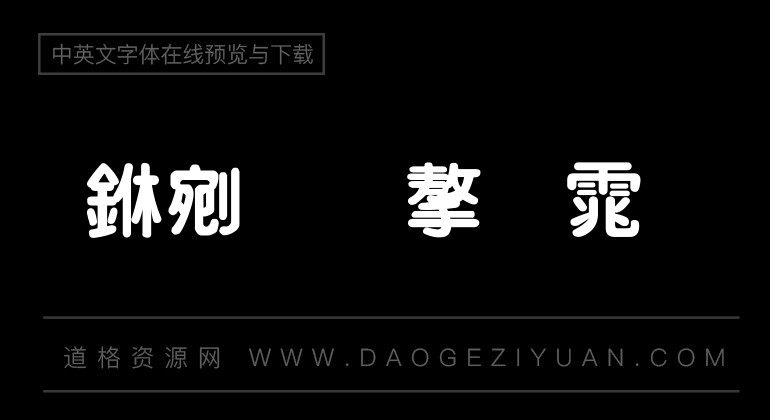
书法家叠圆体
书法家叠圆体,又称“叠圆体”,是由中国书法家叠肖拉克(1890-1965)创作的一种书法字体。它是以“叠”字为主体,将“叠”字的横线、垂线和拱形结合在一起,形成一种有规律的圆形字体。叠圆体字体比较简洁,字形结构紧凑,有良好的空间美感,极具特色。叠圆体字体适合用于书法、楷书、行书、隶书等各种书体中,具有很高的艺术价值。
书法家叠圆体是一款非常不错的手写艺术字体,具有很好的视觉感,适合于文化类的宣传设计、商业类品牌的广告和产品包装设计以及个性化文字排版等较多场景。